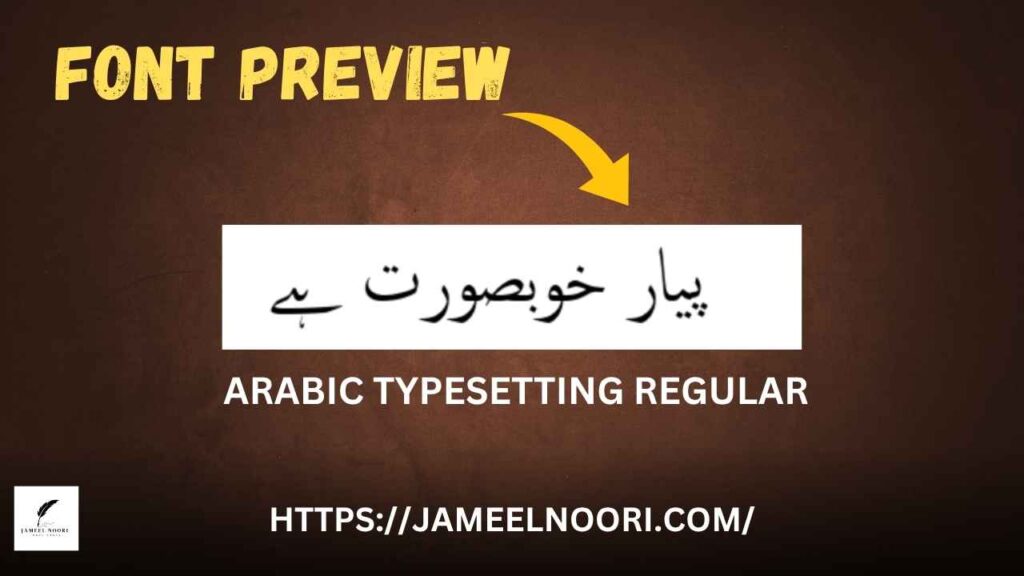
Arabic Typesetting Regular Font download Kia Hai?
Arabic Typesetting Regula font download aik mashhoor aur classic TrueType font hai jo Urdu aur Arabic typing ke liye use hota hai. Iska clean, elegant aur readable design isay printing aur digital documents dono ke liye behtareen banata hai.
Arabic Typesetting Regular Font Kyu Istemaal Karein?
H3: Font ki Khaas Baatain:
- Readability: Asaan aur saaf likhai
- Multi-Language Support: Urdu, Arabic, aur English letters support karta hai
- Professional Look: Official documents ke liye perfect
Is Font Ka Istemaal Kahan Kiya Jata Hai?
H3: Common Use Cases
- Official documents
- Quranic scripts
- Arabic assignments
- Urdu calligraphy
- Social media posts
- Graphic designing
- Urdu quotes
Arabic Typesetting vs Jameel Noori Nastaleeq
Feature | Arabic Typesetting | Jameel Noori Nastaleeq |
Font Style | Regular Arabic/Urdu | Nastaleeq style |
Purpose | Typing & documents | Calligraphy & design |
Agar aapko stylish aur artistic font chahiye to Jameel Noori Nastaleeq choose karein. Lekin agar readable aur clean layout chahiye to Arabic Typesetting best hai.
Is font ka design kaisa hai?
Design simple aur readable hai – especially for professional Arabic/Urdu documents.